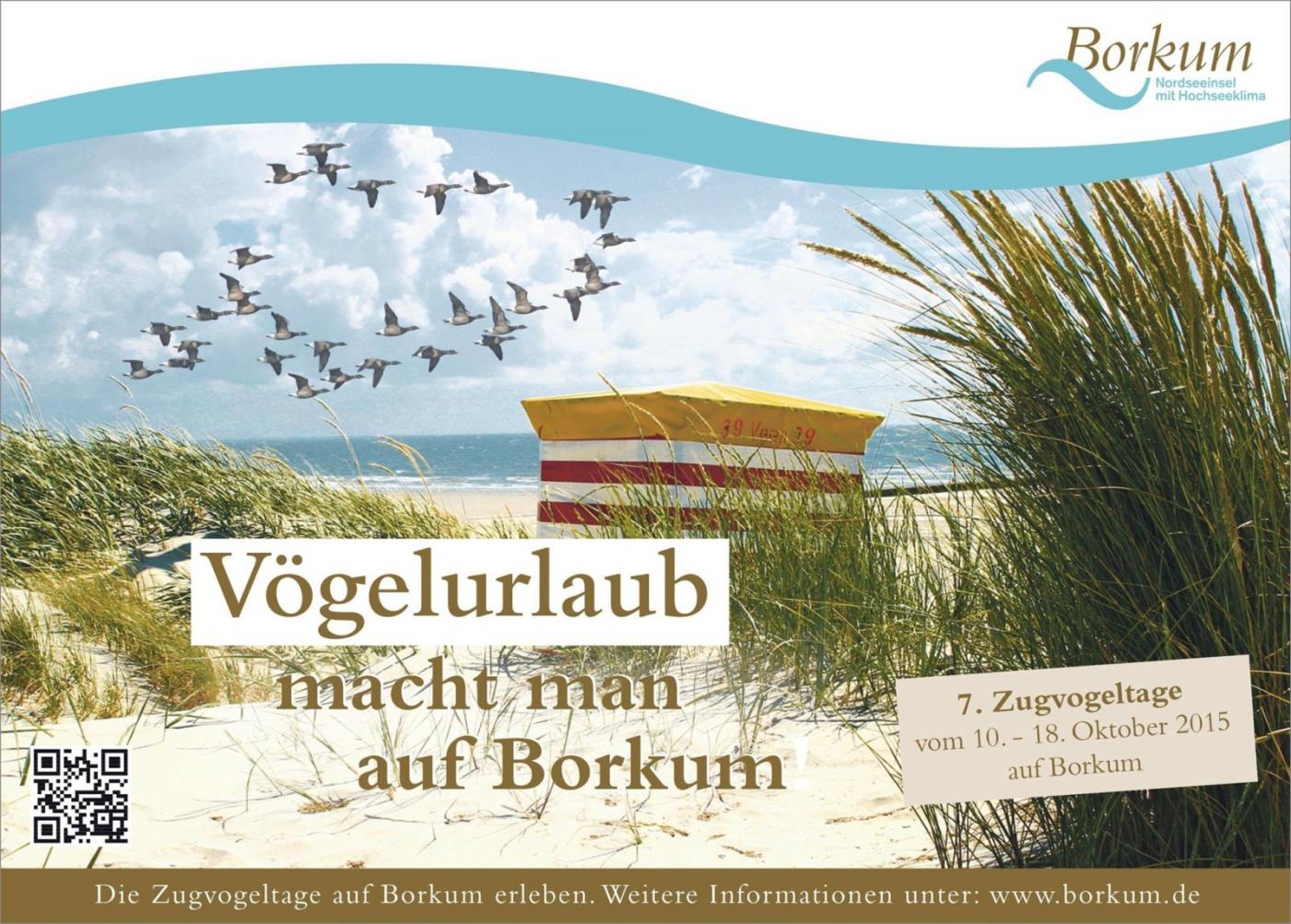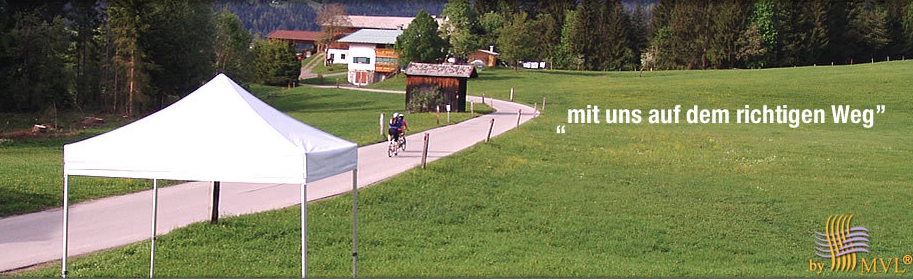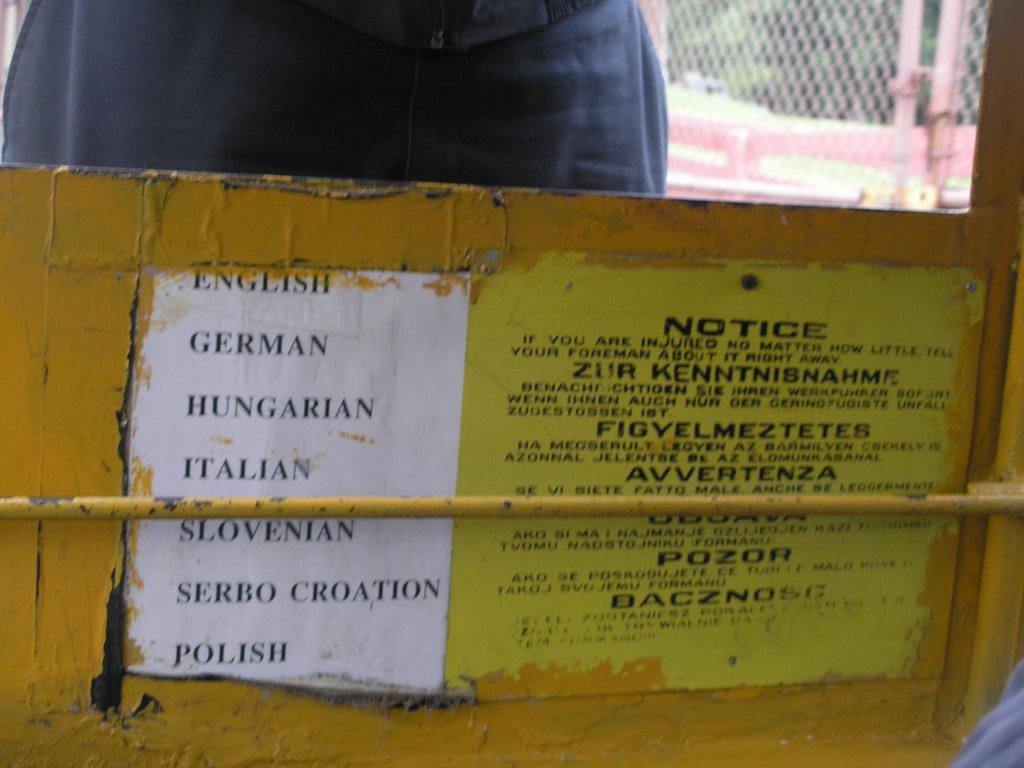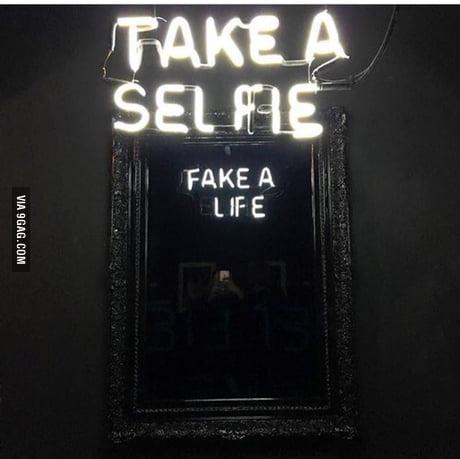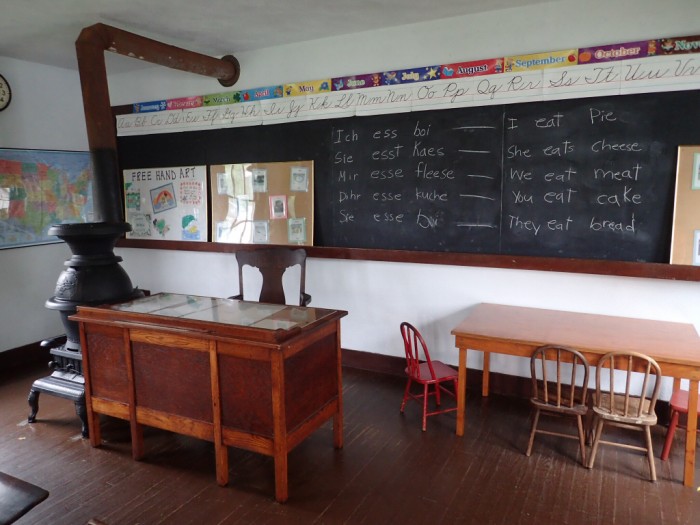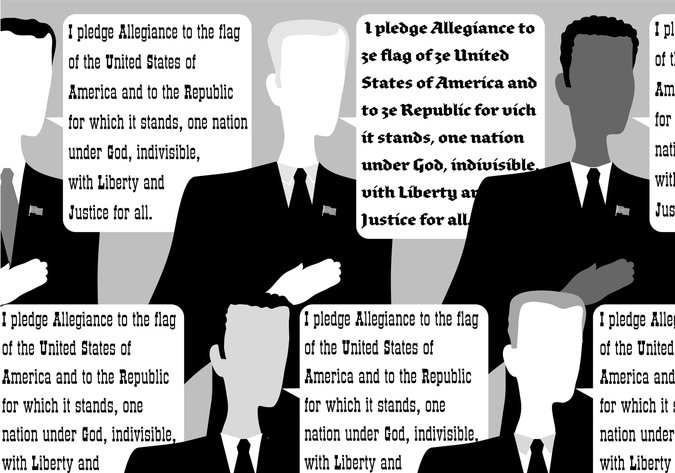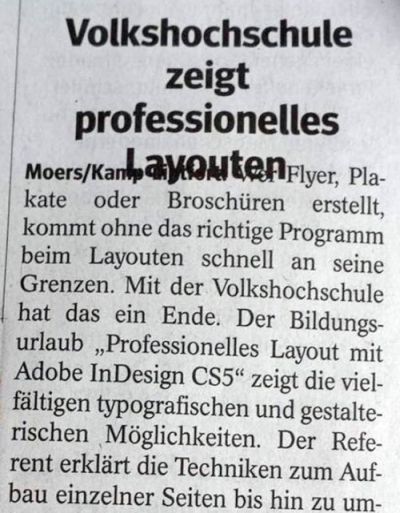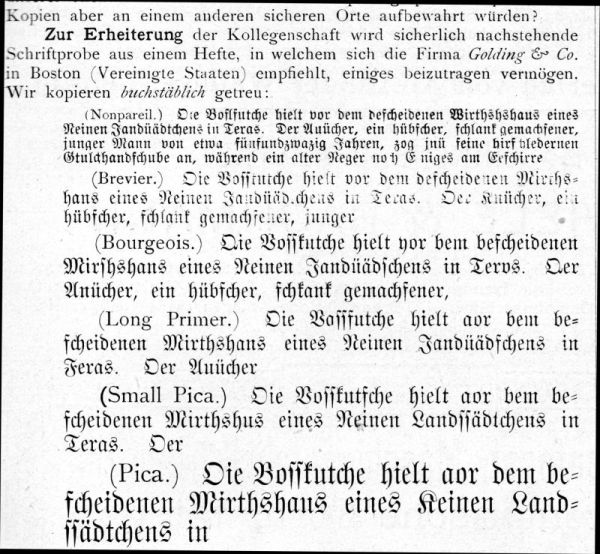
Noch bis morgen:
Die Jugendlichen kann man so lange ja mit Selfies beschäftigen ;-)
Also in kleinschreibung wäre das jetzt lustiger gewesen. Da soll noch mal einer sagen, sie böte keine vorteile! :hammer:
Dazu passt vielleicht dieses gelbe Schild zum Arbeitsschutz, das so noch bis vor einigen Jahrzehnten hundert- oder gar tausendfach in den Kohlebergwerken Nordost-Pennsylvanias hing:
(Die weiße Erklärung links daneben wurde natürlich erst nachträglich vom Bergwerksmuseum angebracht.)
Was den Inhalt des Artikels angeht, haben die beiden Weltkriege den Rückgang der Deutschsprachigkeit in Amerika zweifellos beschleunigt, aber keinesfalls verursacht. Die Nachfahren der ungarischen, italienischen, slowenischen, serbischen, kroatischen und polnischen Bergleute sind heute – genau wie die Nachfahren der deutschen – überwiegend einsprachig. Bei den Nachfahren der nach Deutschland eingewanderten Hugenotten ist das nicht anders. In ein, zwei Genrationen wird es bei den Nachfahren der deutschen Gastarbeitergeneration auch so sein. Da waren und sind überall dieselben Prozesse am Werk.
Großes Ohrenkino! (Ich musste es mir laut vorlesen, um heraus zu knobeln, was wohl eine Bosskutsche sein könnte.) Es gibt übrigens deutsche Dialekte nahe meiner Heimat, die man (von den Ungereimtheiten zwischen den einzelnen Zeilen abgesehen) phonetisch fast so schreiben könnte, da Konsonanten wie t oder v fast oder komplett verschwinden.
Die Boß’kutsche ’oar …
Auch ’ne Möglichkeit! Die kaum standardisierte und stark phonetische Ad-hoc-Schreibung pennsylvaniadeutscher Dialekte mutet, besonders bei älteren Schriften, teilweise recht abenteuerlich an. (Heute gibt es natürlich auch Bestrebungen, das zu standardisieren.) Diesen Aufkleber sieht man in Südost-Pennsylvania übrigens oft:
Gerade bei Facebook in der Timeline gehabt:
Eine arabische Reporter?  :hammer:  :ilovetype:
Da letzte Nacht meine mobile Schilder-Imbiss-Garage sich dem Sturm gebeugt hatte, bin ich auf der Suche nach einem neuen, stabileren Pavillon. Gefunden habe ich das:
Wie passiert sowas?  :-?  :oops:
Ganz einfach:
1. Text-auf-Bilder-Schubser benutzt seit Jahren die "normalen" Anführungszeichen. Wären die auf der Tastatur, wenn sie falsch wären? Schachmatt, Besserwisser!
2. »Exotischer« Kunde verlangt die komisch krummen.
3. Na gut.
Ich sehe hier ständig falschrumme Anführungszeichen, auf Schildern, Bannern, geplotteten Klebebuchstaben … . Immerhin sitzen sie hierzulande wenigstens meistens oben, aber ob nun 66, 99 (richtig herum oder gespiegelt) ist oft Glückssache.
... und dann fallen die gleich runter  8-)
Das sieht ja schon fast so aus, als wären das die normalen Schließenden nur in der nächsten Zeile  :-?